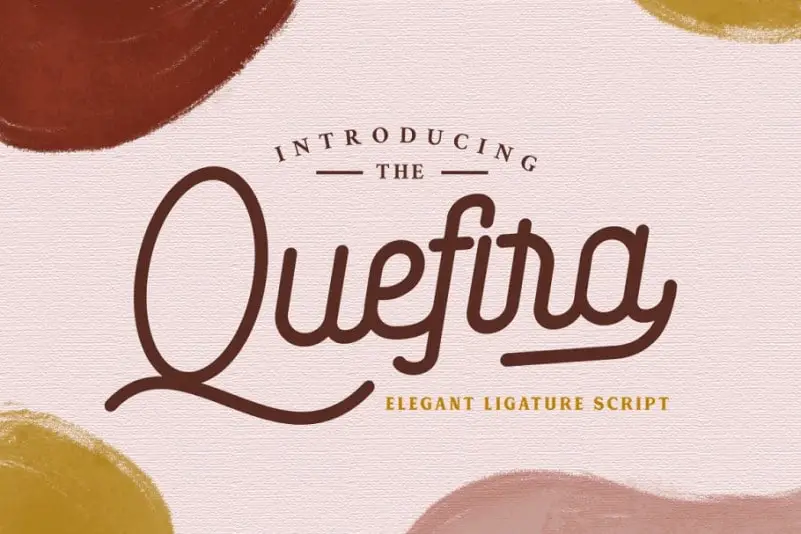
Quefira Script Font – Download Grátis
A Quefira Script Font é uma nova tipografia vintage que oferece um equilíbrio perfeito entre sans-serif e script fonts para estilos retro-vintage. Foi cuidadosamente projetada para se adequar a cada projeto, destacando sua estrutura limpa e minimalista enquanto mantém suas ligaturas e alternativas de fonte lindas. Suas letras são puras e naturais, com um traço que transmite uma sensação de naturalidade em seus designs. Ela é ideal tanto para criar logotipos quanto para textos como citações, bem como para embalagens ou rótulos de produtos, mensagens para camisetas e muito mais. Engajante e versátil, a Quefira Script Font é uma escolha incrível para quem busca um toque vintage moderno em seus projetos visuais.